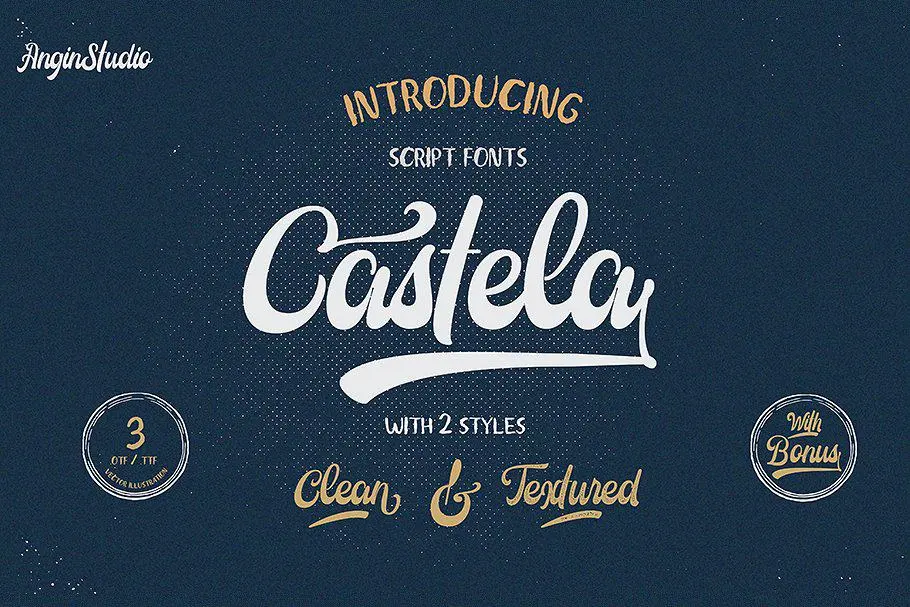
A Castela Font é uma elegante fonte script que transmite um verdadeiro toque pessoal aos seus projetos gráficos. Esta fonte foi criada com detalhes cuidadosamente trazendo a sensação de frescor e modernidade dos enfeites tradicionais. Perfeitamente adaptável para diversos usos, como design editorial, marca, citações artísticas, capas de livros ou posters, desenho de roupas, embalagens de produtos, etiquetas, eventos especiais ou qualquer coisa que exija o toque delicado e único de uma fonte criada à mão. A Castela é perfeita para quando você quer um toque especial em seus materiais gráficos, seja ele uma capa de livro com um texto elegante e sofisticado, uma etiqueta cuidadosamente personalizada ou até mesmo um adesivo feito à mão para seu produto.